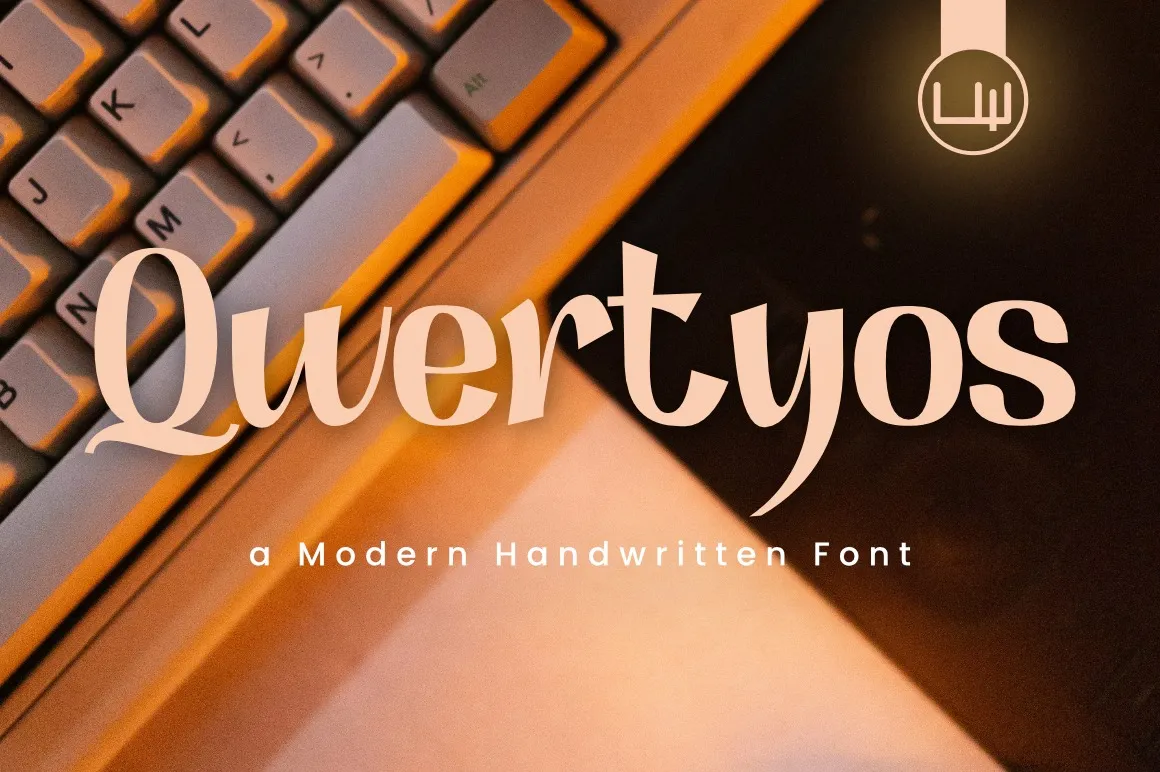
Qwertyos Font – Fonte Grátis
Qwertyos Font
A Qwertyos Font é uma elegante mistura entre modernidade e clássico, ideal para estilos visuais criativos. Com seu próprio estilo único e aspecto contemporâneo, essa fonte traz curvas encantadoras e padrões satisfatórios para as famosas tipografias grossas tradicionais. Seu design perfeito para cartas de convite, cartazes, marcas ou qualquer outro tipo de anúncio, a Qwertyos é uma escolha incrível para designers que buscam adicionar um toque autêntico e elegante em seus projetos visuais modernos. Através da sua utilização, você pode criar designs vibrantes e memoráveis, tornando cada projeto especial.